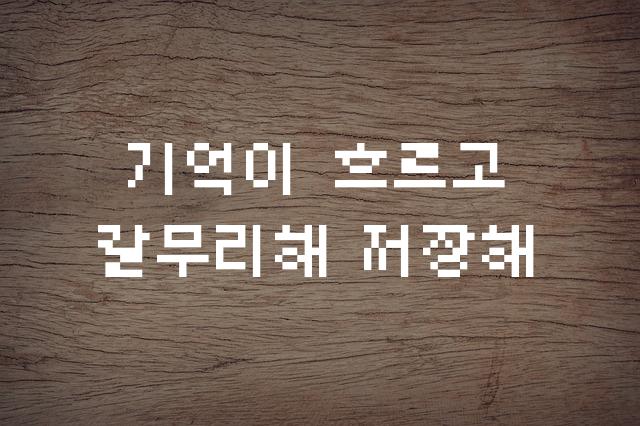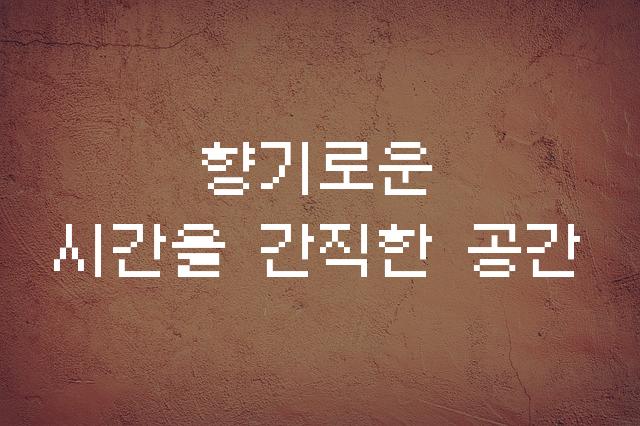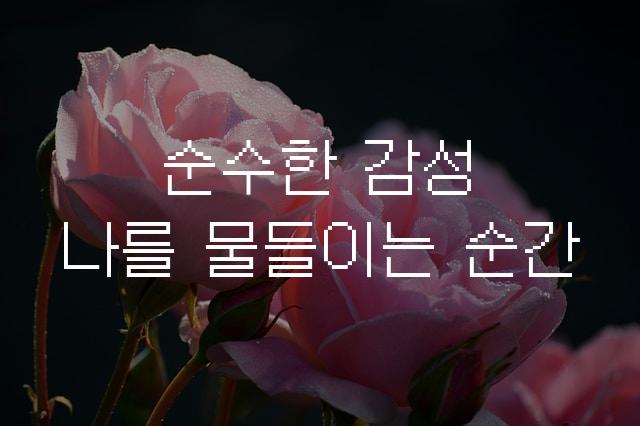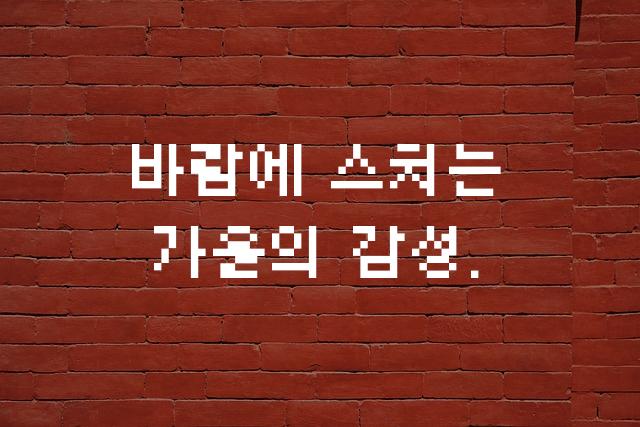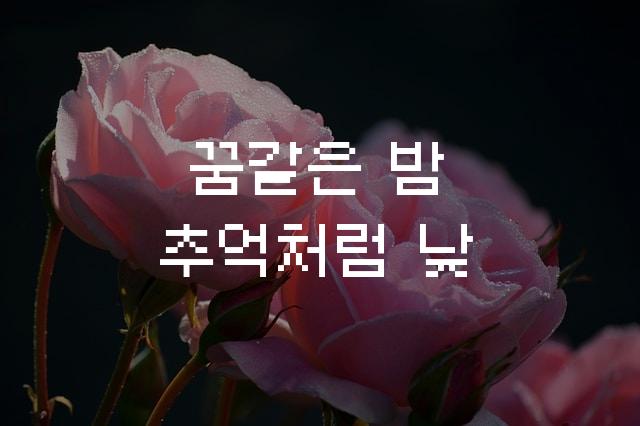
갈무리모노11은 Lee Minseo에 의해 제작된 현대적인 모노스페이스 폰트로, 깔끔하고 고정된 글자 간격이 특징입니다. 디지털 작업 환경에 최적화되어 있으며, 감정적으로는 안정감과 집중을 불러일으키는 디자인입니다.
갈무리모노11은(는)
계열의 생김새를 가지고 있으며
출판 디자인, 출판물 제목, 일기/편지 등에서 자주 활용되며, 효과적인 메시지 전달에 적합합니다.
이 폰트는 출판/미디어, 문화/예술, 유아/가족 분야에 잘 어울리며,
감성적인, 부드러운, 예술적인 느낌을 담고 있는 것이 특징입니다.
이 폰트와 유사한 폰트로는 Roboto Mono, Source Code Pro, Fira Code 등이 있어요. 함께 비교해 보시면 좋습니다!